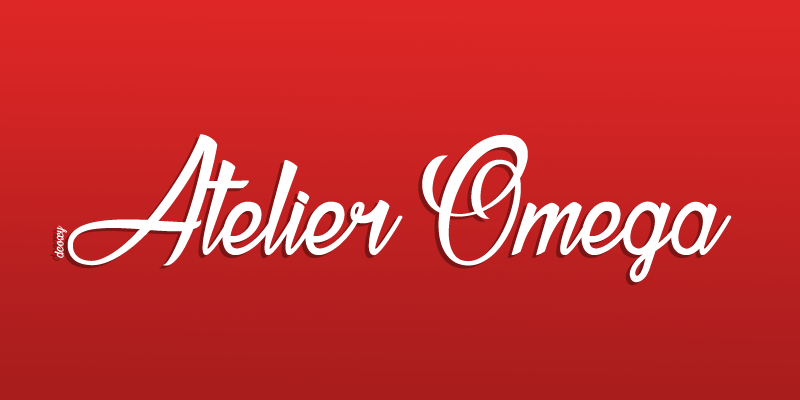
A fonte ‘Atelier Omega Font’ é uma elegante escolha para quem busca um estilo cuidadosamente trabalhado na tipografia. Desenvolvida pelo designer Hamilton, essa fonte é perfeita para trabalho de autógrafos e escrita por conta própria. O design único mantém alegria e sofisticação, ideal para qualquer projeto que busque uma aparência única e refinada. Importante notar que um licenciamento é necessário para uso comercial ou promocional. Para obter mais informações sobre como usar essa fonte de forma legal, entre em contato conosco através do email: